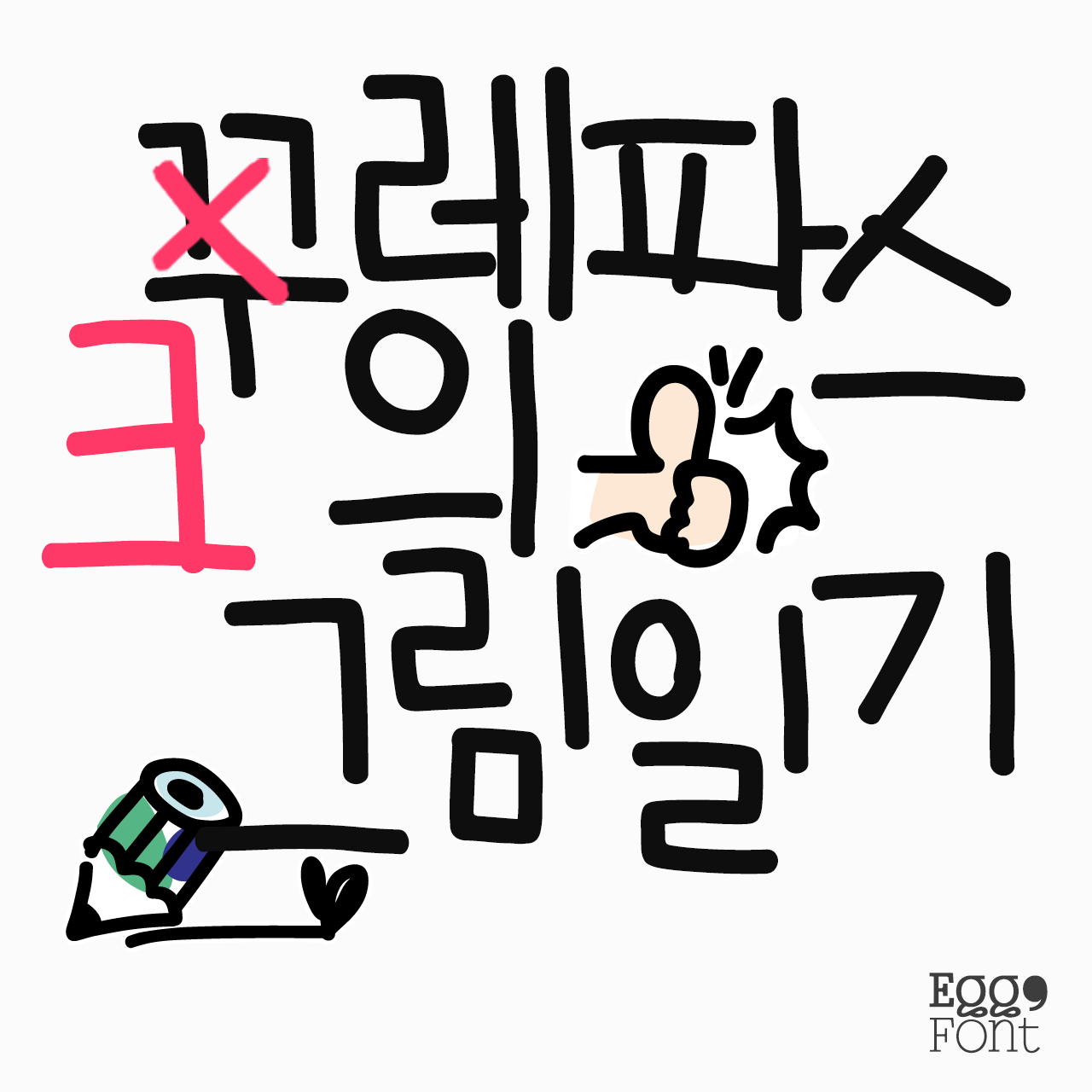
PPT용
산돌
SD 그레타산스
「SD 그레타산스」는 책표지나 포스터에 크게 사용되는 제목용부터, 영상 자막, 비교적 장문의 텍스트 조판까지! 폭넓은 활용도를 지닌 종횡무진 활약상을 보여주는 폰트입니다. 이 폰트 하나만으로 이목을 끄는 깔끔한 프레젠테이션을 완성할 수 있어요.
타입세트컴퍼니
TSC핫플고딕
「TSC핫플고딕」은 꽉 찬 네모꼴 구조의 고딕 폰트입니다. 넓은 자폭을 가져 제목용으로 사용할 때 좋은 효과를 볼 수 있으며 장난스러우면서도 곧게 뻗어있는 획이 특징입니다. 복고풍 느낌 또는 무거운 인상보다는 밝고 경쾌한 분위기를 띄어요.
레포트용
산돌
SD 노벰버
「SD 노벰버」는 도로 표지판과 같은 정보전달 시스템에 적합한 실용적인 폰트입니다. 높은 가독성이 특징으로, 긴 텍스트와 작은 크기의 본문에도 사용하기 좋습니다. 「SD 노벰버」의 모든 획 끝은 항상 직선으로 끝나도록 설계되는데요, 이 장치는 글자와 글자 간의 연계성을 강화시키며 뚜렷한 흰 공간을 만듭니다.
한글씨
HG인문고딕
「HG인문고딕」은 새로운 본문용 한글 고딕 서체를 기획한 결과물입니다. 기존의 고딕 구조와 차별화되어 디자인되었으며 그로 인해 자소의 형태에서 손글씨적인 특징을 찾아 볼 수 있습니다. 부드럽고 연하게 읽히는 글에 섬세함을 더해 줄 폰트랍니다.
행사용
티랩
Tlab퓨처
「Tlab퓨처」는 심플하고 본질적인 획으로 한글의 기하학적인 형태를 부각하는 폰트입니다. <정원>의 형태를 유지하면서 각 자소에 맞게 크기를 변화하는 ‘이응’의 글자 구조와 글자 꼴마다 달라지는 자폭의 차이로 제작물의 유니크한 매력을 배가할 수 있습니다.
디자인210
210 수퍼사이즈
「210 수퍼사이즈」는 기울기와 3D 효과를 적용하여 다양한 분야에서 주목성을 가지도록 강한 이미지를 컨셉으로 한 폰트입니다. 두께감 있는 획과 네모틀 안에 꽉 찬 디자인에서는 무게감이 드러난답니다. 강렬한 「210 수퍼사이즈」로 보는 이들의 눈길을 사로잡아보세요.
브래너스
BeOkay
「BeOkay」는 모던하고 정교한 형태를 보이는 영문 디스플레이 폰트입니다. 폰트 자체만으로 독특한 개성을 지니고 있어, 헤드라인, 로고, 브랜딩 작업에 사용될 수 있습니다. 특이한 모양을 띄는 알파벳들을 찾아내어 적절한 조합으로 매력있는 작품을 완성해 보세요.
영상용
산돌
Sandoll 호요요2
「Sandoll 호요요2」는 예측할 수 없이 들쭉날쭉한 글자 폭이 가장 큰 특징인 가편폭 폰트입니다. 광고, 영상 썸네일과 자막, 패키지 등에서 꾸준히 활용되어 한번쯤은 마주쳤을 거예요. 평범한 브이로그에 귀엽고 유쾌한 분위기를 더하고 싶다면 「Sandoll 호요요2」를 자막 폰트로 사용해 보세요.
준폰트
오케스트라
「오케스트라」는 클래식 음악의 다양한 빠르기에 따라 달라지는 곡의 분위기와 느낌을 표현한 폰트입니다. 지휘자의 손동작에 맞춰 연주자들도 박자 조절을 하듯이 특징을 단계별로 부여했으며 글자수가 많으면 느린 템포를, 글자 수가 적으면 빠른 템포를 사용하면 좋습니다. 화려한 인트로에 활용해 보세요.
타이포디자인연구소
타이포_토토시네마
「타이포_토토시네마」는 영상 자막으로 사용하기 위해 제작된 손글씨 서체로 다양하고 많은 발음을 표현할 수 있는 폰트입니다. 4종의 굵기로 제작되어 사용자의 기호와 영상의 톤앤 매너에 맞게 사용할 수 있습니다. 오른쪽 위로 살짝 올라가며 기울어진 것이 특징입니다.
취미용
다인의 글씨
Dain 호빵인줄알았어요
「Dain 호빵인줄알았어요」는 넓적하고 쫀득한 질감이 느껴지는 손글씨 폰트입니다. 폭신하고 쫀득하고 푸근따땃한 호빵의 텍스처를 담아 귀여운 분위기를 풍기네요. 경쾌한 분위기로 다양한 곳에서 어울리게 사용할 수 있답니다.
에그구폰트
Egg9꾸레파스의그림일기
「Egg9꾸레파스의그림일기」는 아기자기한 손글씨 폰트입니다. 들쑥날쑥 삐뚤빼뚤 춤을 추는 것만 같은 모습이 귀엽고 사랑스럽습니다. 그림일기라는 이름이 곧잘 어울려 모바일 일기장***을 쓰기에도 좋겠네요. ;> , ;) , :!: , :?: 를 입력하여 히든 딩벳을 확인해 보세요.